神話や建築からインスピレーションを得たフォント
Blaze Type
Matthieu Salvaggio
Blaze Typeの創立者でタイプデザイナーのMatthieu Salvaggio氏にお話を聞きました。
1. Blaze Typeについて教えてください。
Blaze Typeはフランスの独立系タイプファウンダリーで、コンテンポラリーなリテールフォントとカスタムフォントの制作に力を入れています。デザイン的にも技術的にも高品質なフォントを作成し、タイプデザイナーの作品を世に広めることが私たちの目標です。Blaze Typeの特徴は、リリースするフォントが多岐にわたることです。多くの言語に対応し、さまざまな代替文字やスタイルとウエイトの幅広いフォントファミリーを展開しています。神話や建築から多くのインスピレーションを得て、それを元にフォントをデザインしています。
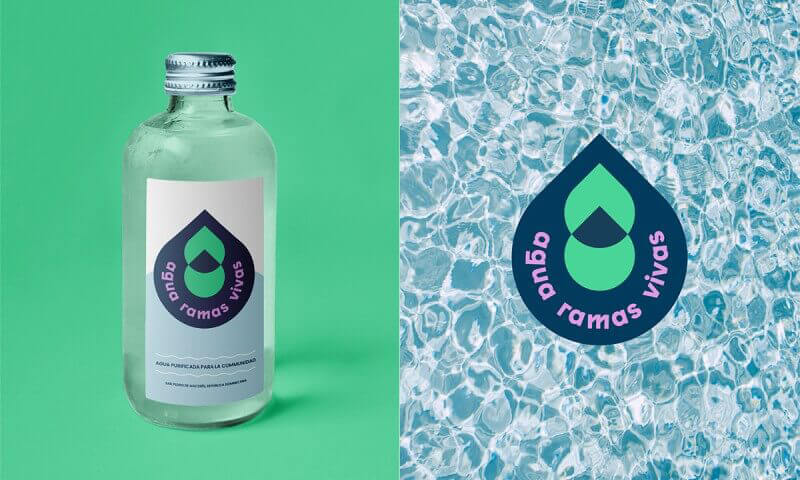
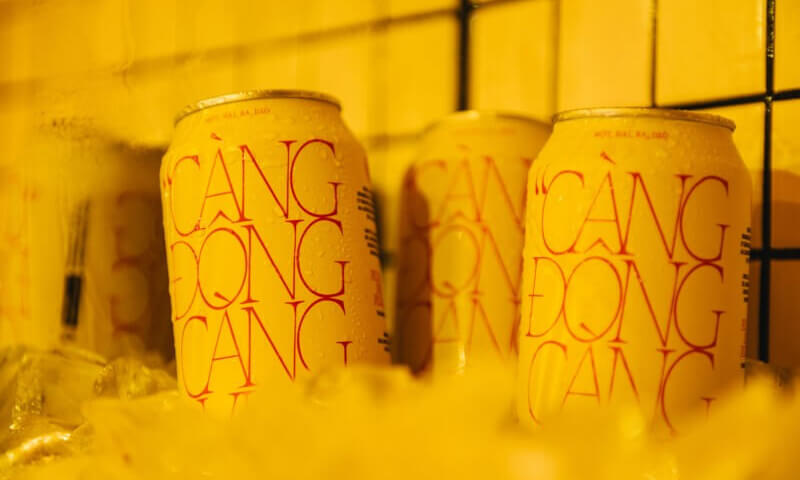
2. Blaze Typeで人気のあるフォントについて教えてください。
『ヨハネの黙示録』からインスピレーションを得たディスプレイ用セリフフォントのApocと、北欧の神話と建築からインスピレーションを得たサンセリフフォントのSurtです。どちらも、あらゆる場面において表現力と使いやすさを発揮する、私たちを特徴づけるフォントファミリーです。
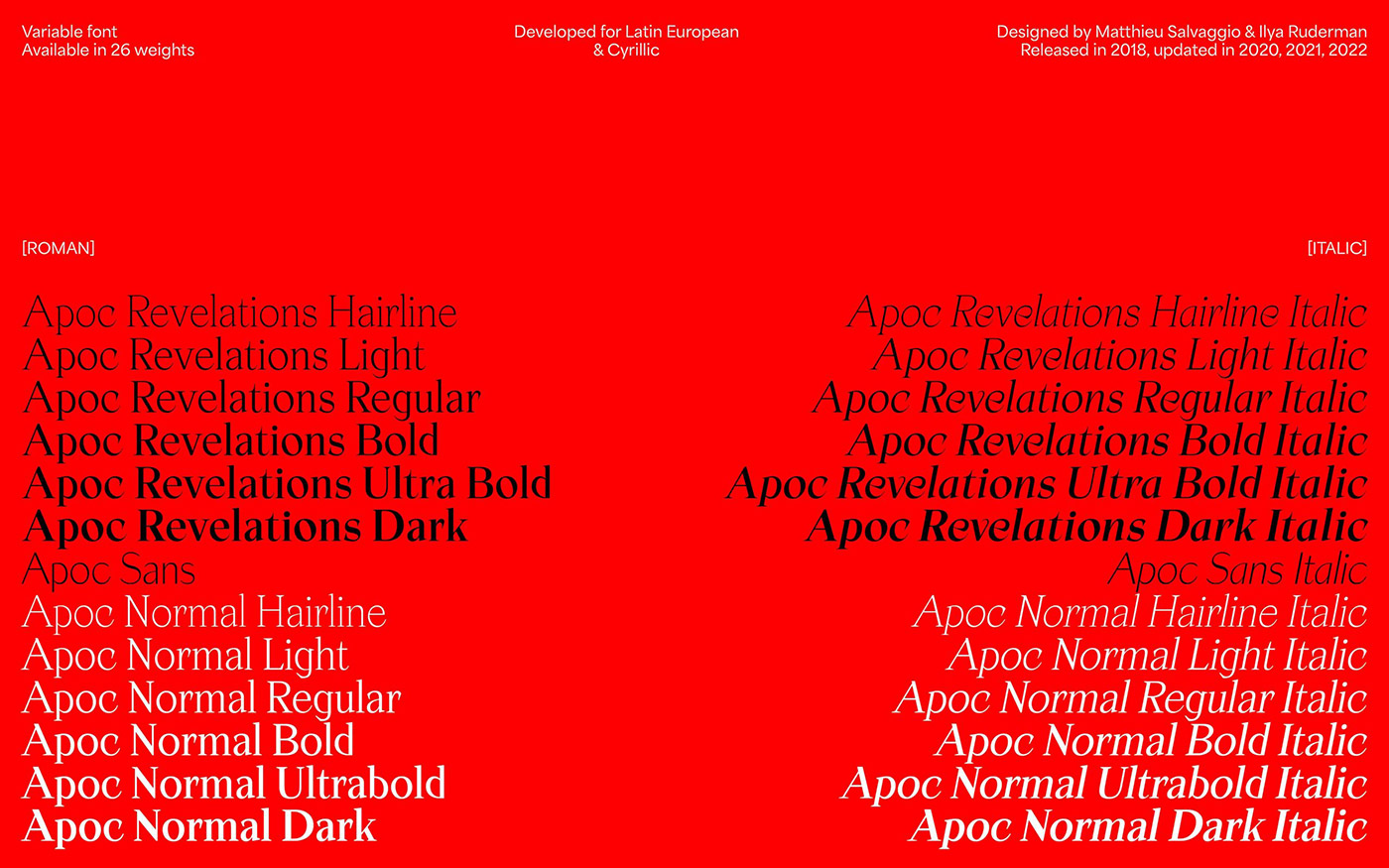
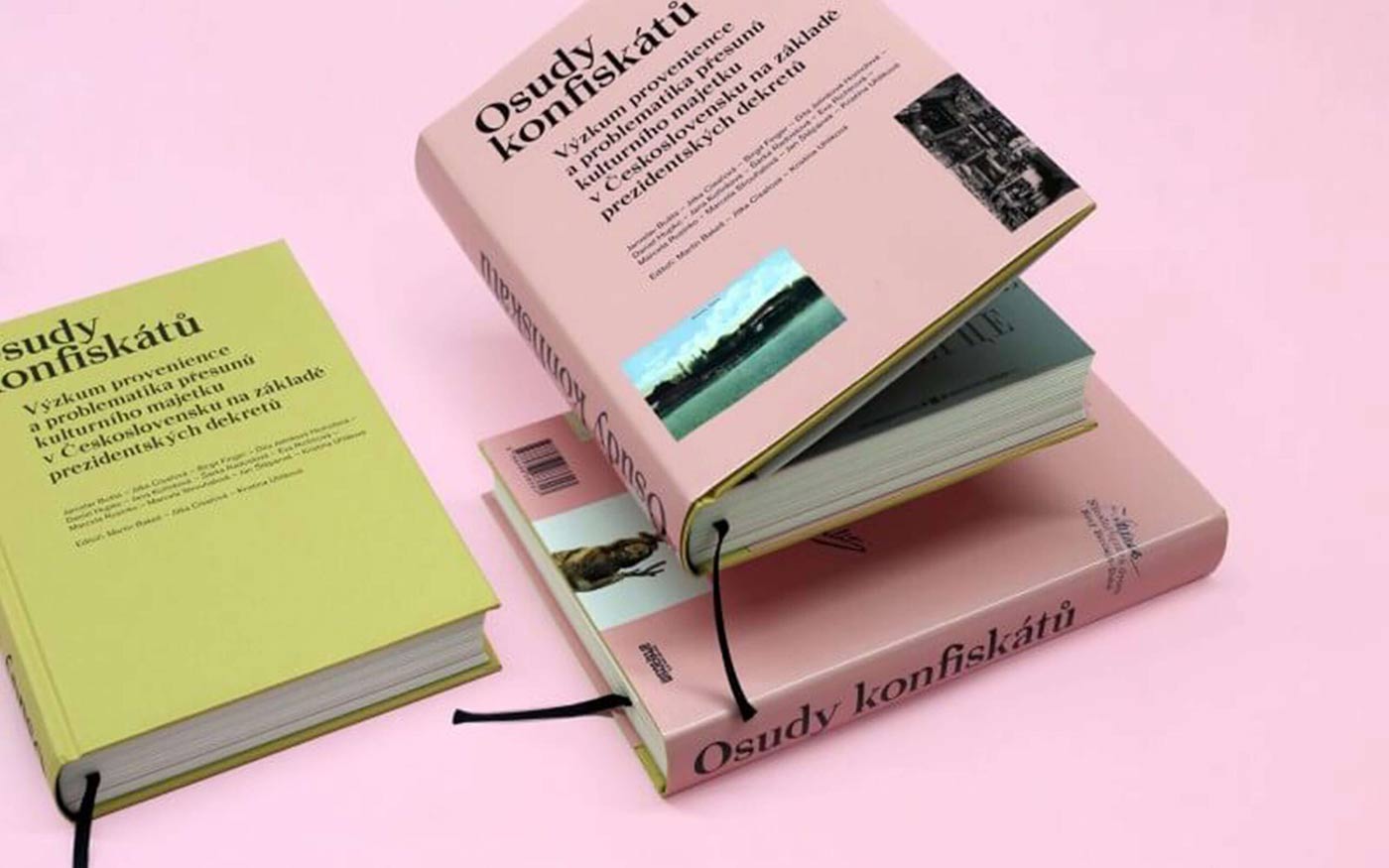
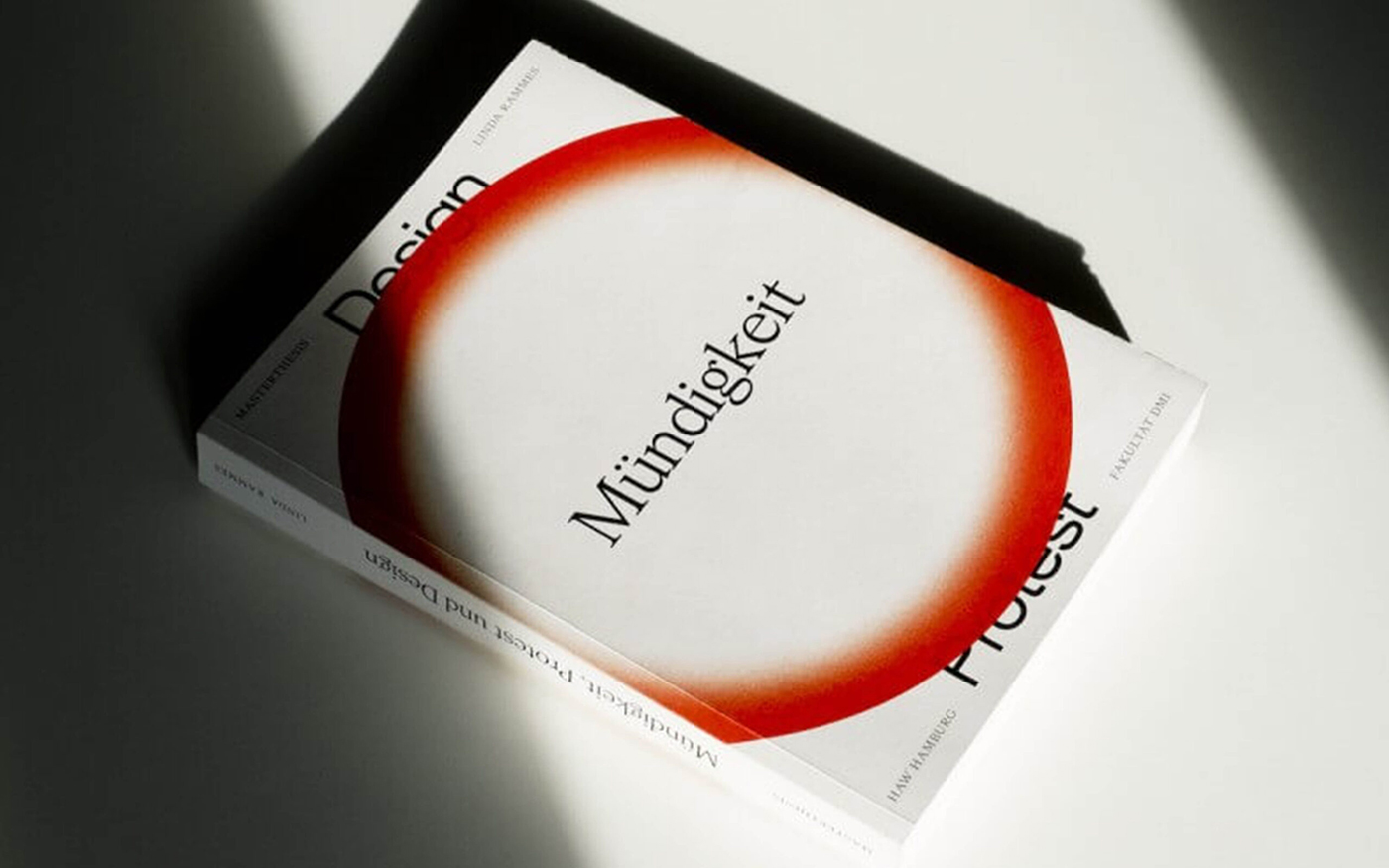
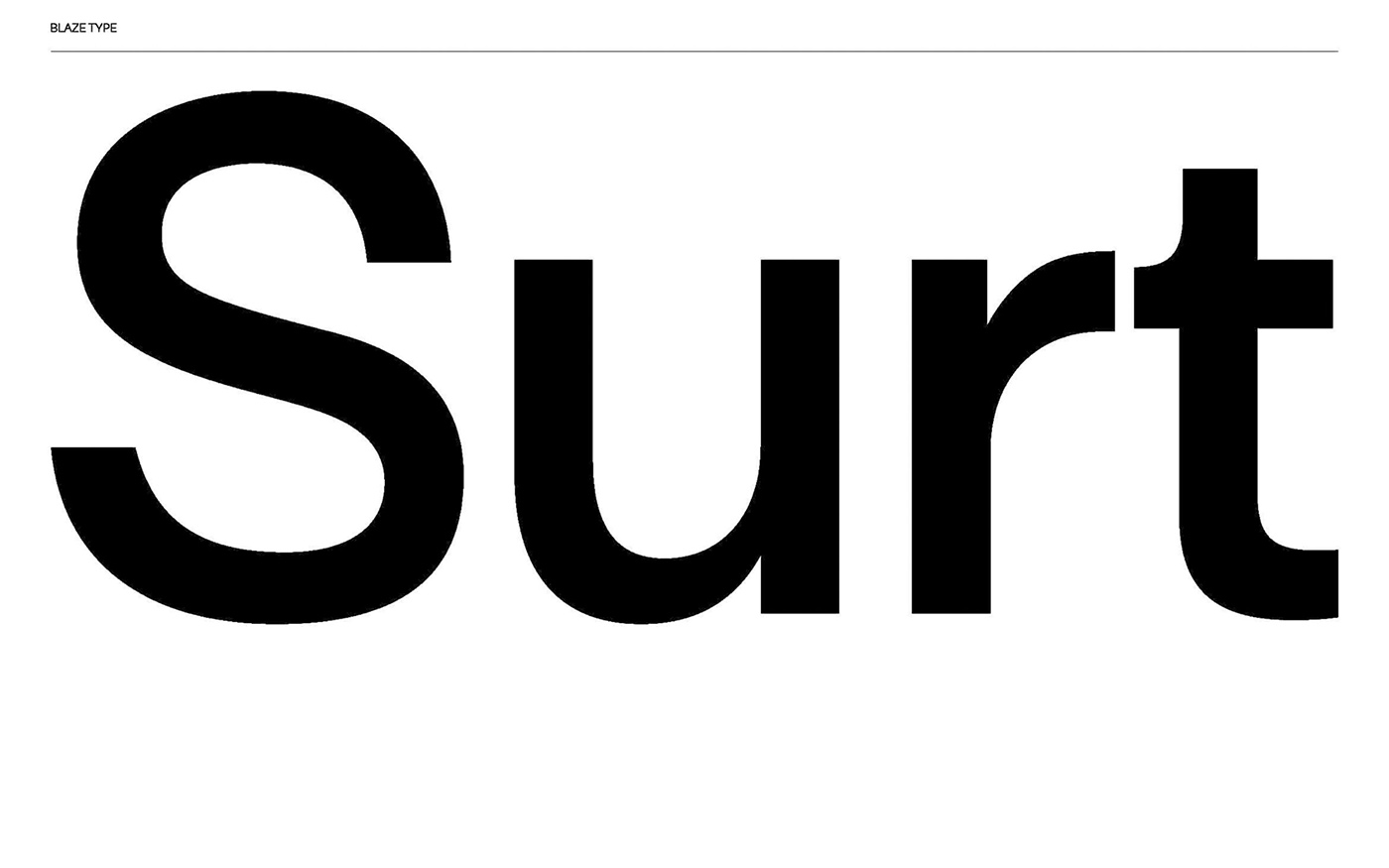
3. 新しくリリースしたフォントはありますか?
毎年、多くのフォントをリリースしています。最新のフォントはHugo JourdanがデザインしたSlussen、そしてLéon HuguesとMatthieu SalvaggioがデザインしたRulesです。
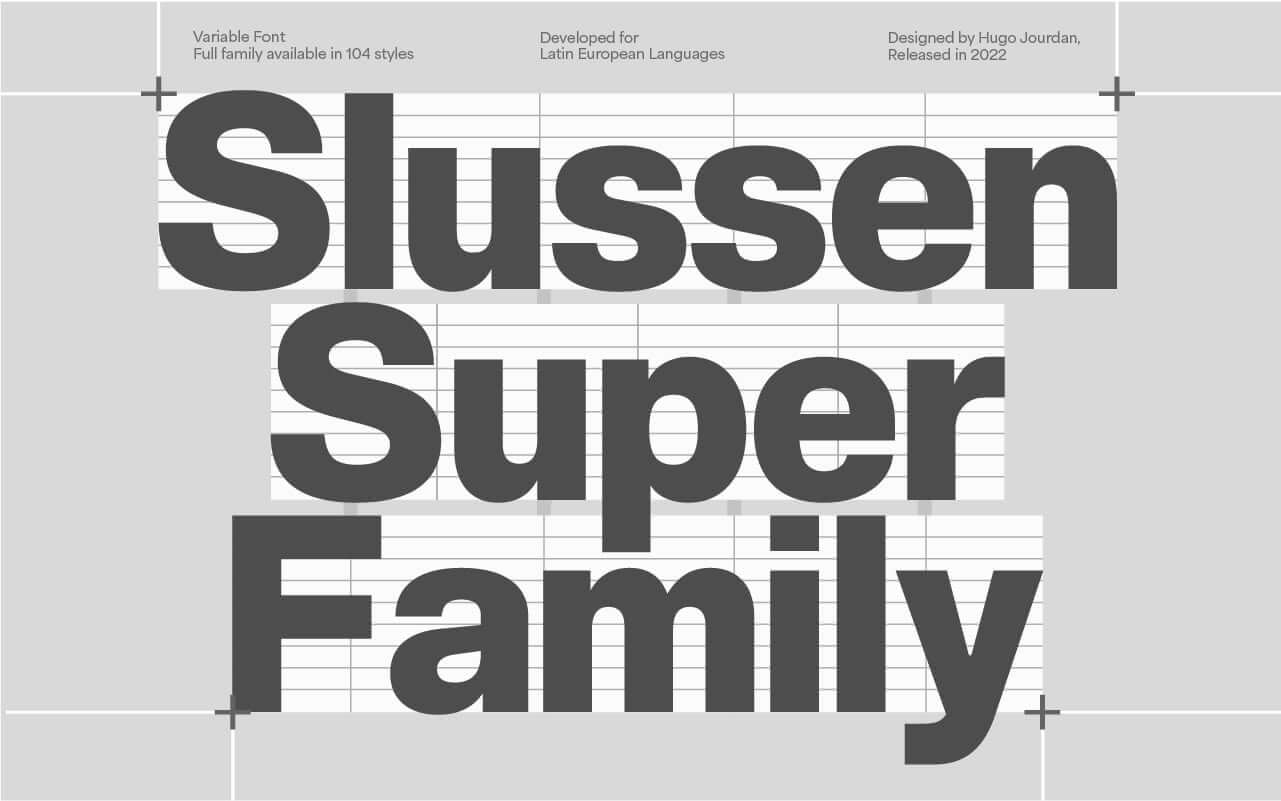
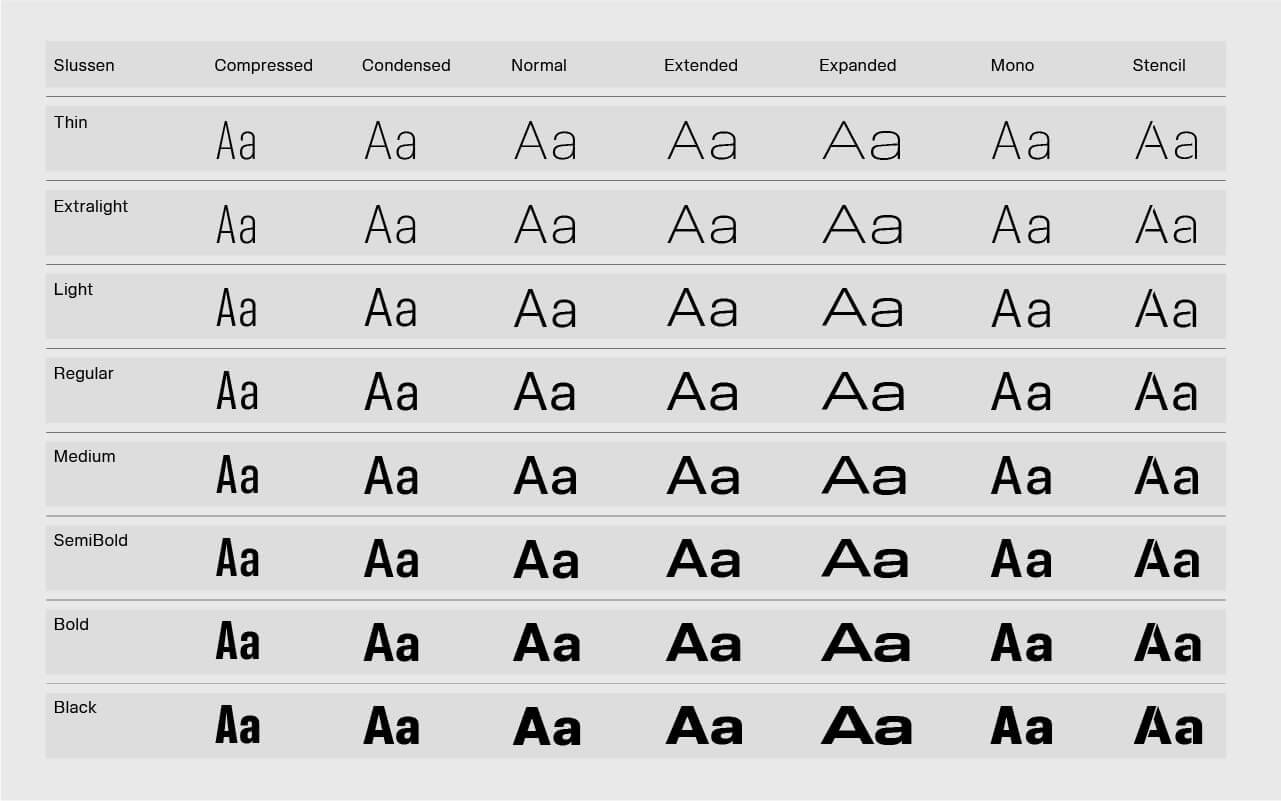
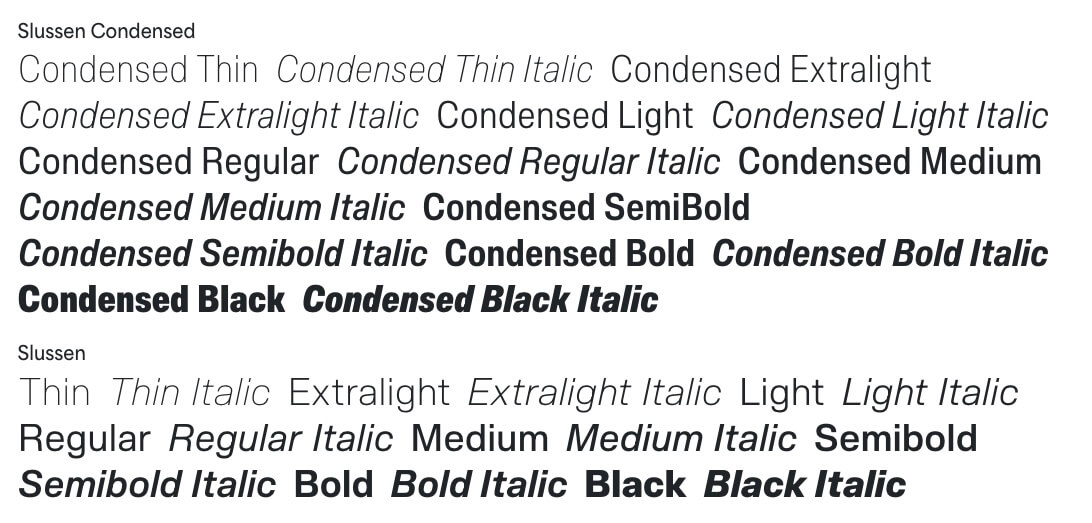
4. オリジナルフォントとカスタムフォント開発の割合はどれくらいですか? また、カスタムフォント開発について教えてください。
毎年、複数のリテールフォントを発売しています。フォントのデザインは完成までに数年かかるものもありますが、常に2つ以上のリテールフォントファミリーを制作するようにしています。
件数は年によって違いますが、毎年クライアントから直接カスタムフォント制作の依頼をいただきます。クライアントのニーズに合わせた多言語フォントを制作したり、ブランドをイメージしたフォントファミリーのためにカスタムフォントを新しくデザインしたり。また、Blaze Typeのフォントをベースに、クライアントのニーズに合わせて変更を加えたカスタムフォントの制作もしますし、カスタムロゴのデザインもします。どのプロジェクトも、まずクライアントのニーズをしっかり把握するための話し合いから始めます。
見た目も使い勝手も良いフォントをデザインするためには、そのフォントがどんなソフトウェアで使われ、どこに表示されるのかなど、クライアントがそのフォントをどのように使いたいのかを理解することが重要です。クライアントがそのフォントを使って最終的に何をしようとしているのかをよく話し合い、理解を深めることで、より質の高いフォントを提供できます。これまでに、Hall & Partnersのブランドフォントや、Ogilvy LabのVolleybal Worldフォントシステム、GraphéineのLe Mont Saint Michelのためのフォントなど、さまざまなクライアントと良い仕事ができました。
5. Blaze Typeのお客様について教えてください。
クライアントは、ほとんどがデザイナーやデザインスタジオ、デザインエージェンシーです。提供するフォントは、ポスター、書籍、ウェブサイト、アプリ、サイネージシステム、そしてビデオインスタレーションなど、ありとあらゆるものに使われます。光栄なことに、Blaze TypeのフォントはPentagramのような有名エージェンシーや世界各地のフリーランスデザイナーに使っていただいています。Blaze Typeのフォントをデザイナーの方々に使っていただくことが私たちの喜びです。私たちのフォントを使った作品を見るのが本当に楽しみです!
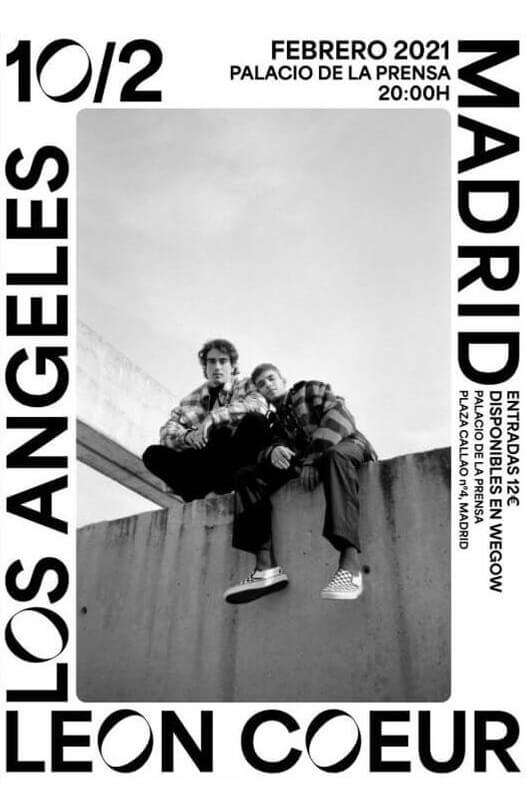
6. フォント業界における御社のポジションと存在意義についてどのように思いますか?
Blaze Typeは2016年に1人でスタートしたところから徐々に成長し、今では世界各地からさまざまなタイプデザイナー、グラフィックデザイナー、モーションデザイナー、デベロッパーが参加しています。現在の主な目標は、世界中の若いフォントデザイナーの作品を世界に広げ、彼らとともに教育やコラボレーション、制作、販売をしていくことです。先ごろ、The Box(https://blazetype.eu/the-box)という小さなファウンダリーを立ち上げました。ここでは才能ある若いデザイナーたちの作品を毎月紹介していく予定です。
7. オープンソースやフリーフォントについてどのように思いますか?
私自身は、誰でも手にすることができて、アップデートや変更を加え、進化させていくプロジェクトというオープンソースの考え方は好きです。オープンソースフォントやフリーフォントが商用フォントの代わりになるとは思っていませんし、それぞれ用途や市場が違います。ただ、ひとつ問題があるとすれば、世の中にはフォントは無料であると考える人がいることです。インターネットで手に入るほとんどのものは簡単にダウンロードして使用でき、無料のように見えるからです。私たちは、フォントが持つ意味やライセンスの存在を理解してもらわなければいけないと考え、そうした点を主張するためにも、Blaze Typeのフォントを適正な価格で公正なライセンスのもとで使っていただけるよう最善を尽くしています。